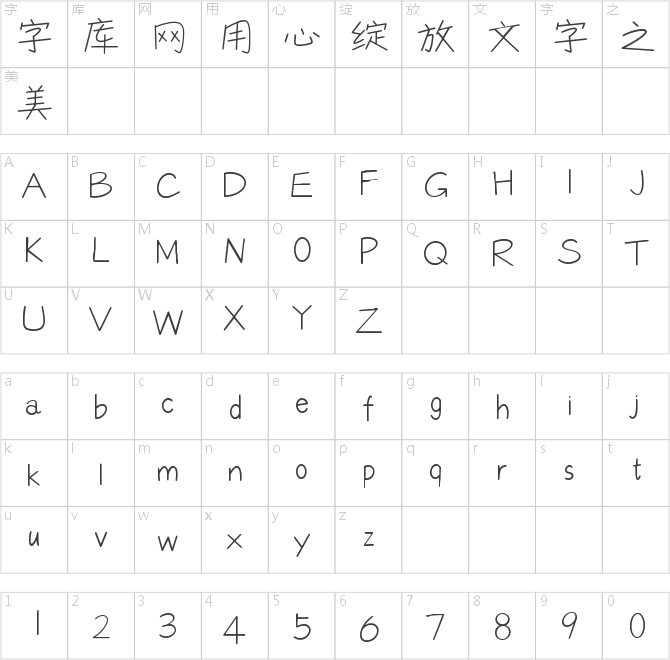
字魂212号-浪漫情书体
字魂212号-浪漫情书体是一款硬笔手写字,字体的起笔、收笔和折笔处呈圆形,笔画圆转流畅,字体结构活泼有趣。适用于品牌广告和产品包装设计,以及社交网络个性化用字。
字魂212号-浪漫情书体字体zihun212hao-langmanqingshuti字库是一款让人赏心悦目、百看不厌的中文字体,适合各类广告和产品包装设计应用,字体大小7.77MB,格式为ttf字体,上传用户是喜欢戳爷,作者/版权方为字魂